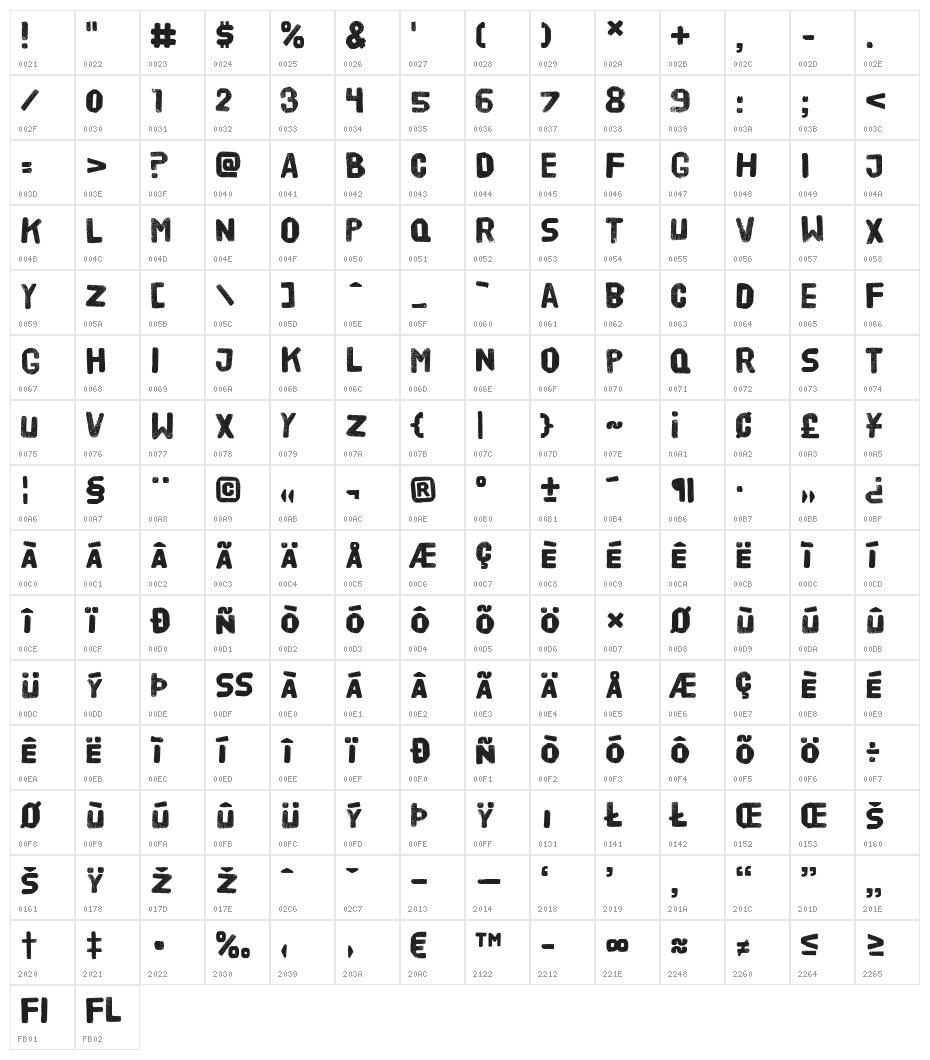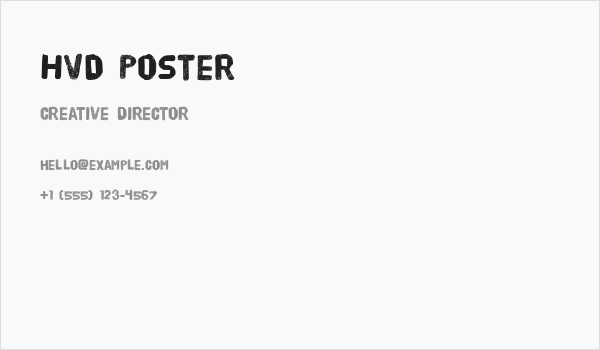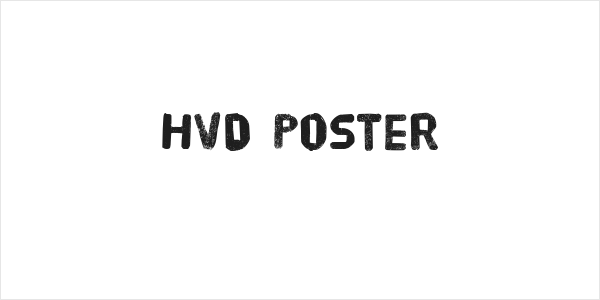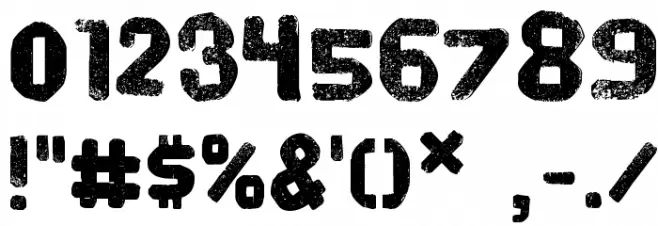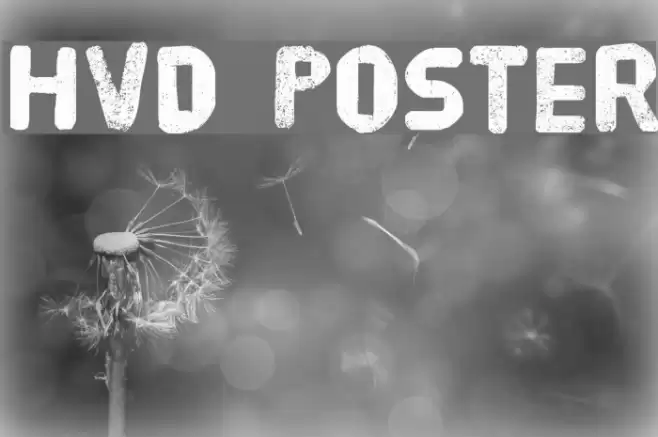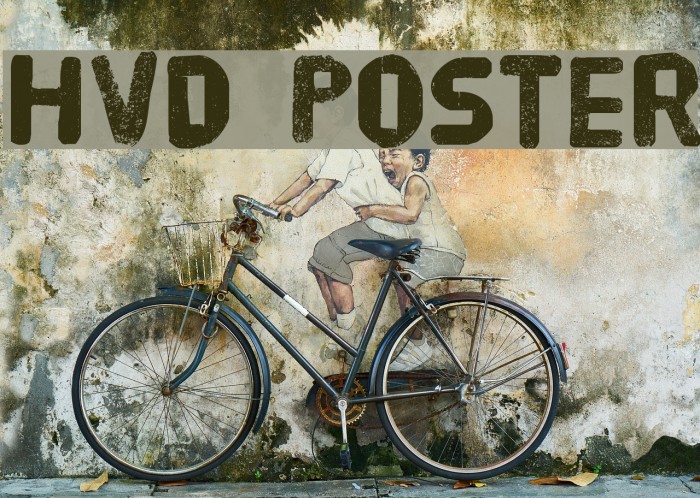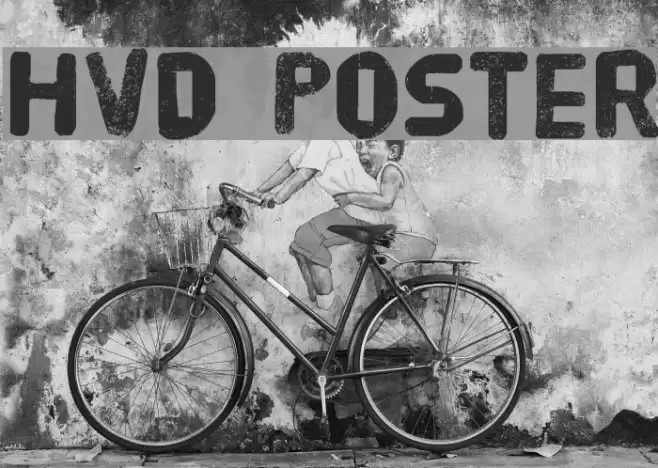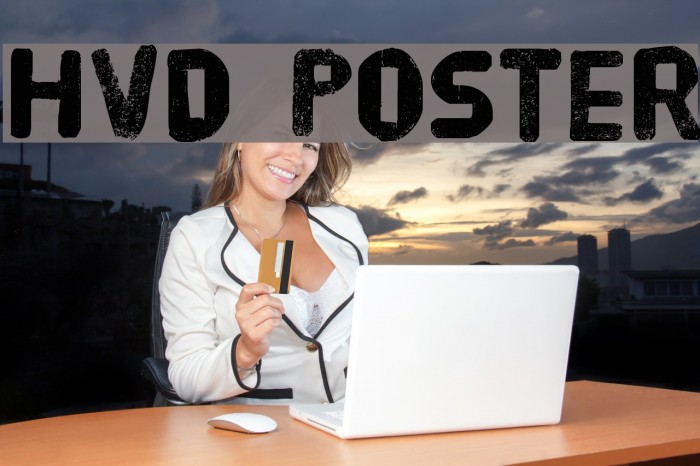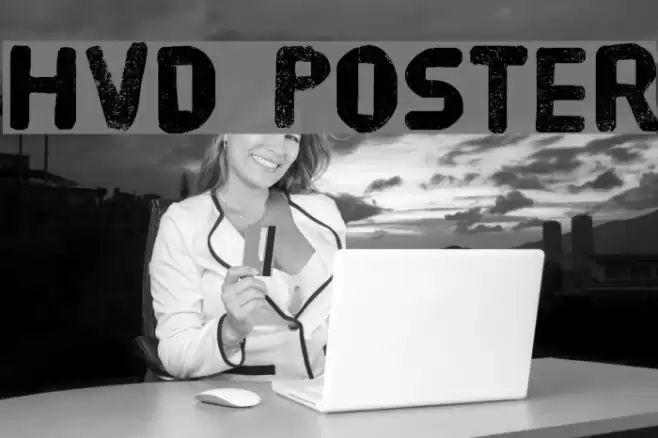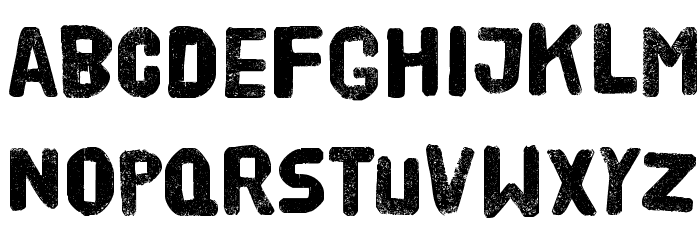
HVD Poster Font
✎ Distorted Eroded
| Категория | Distorted Eroded |
| Общий стиль | Vintage |
| Область применения | Headlines, Posters, Branding |
| Рекомендуемые проекты | Ideal for vintage posters, branding, headlines, and any design needing a bold, rugged look. |